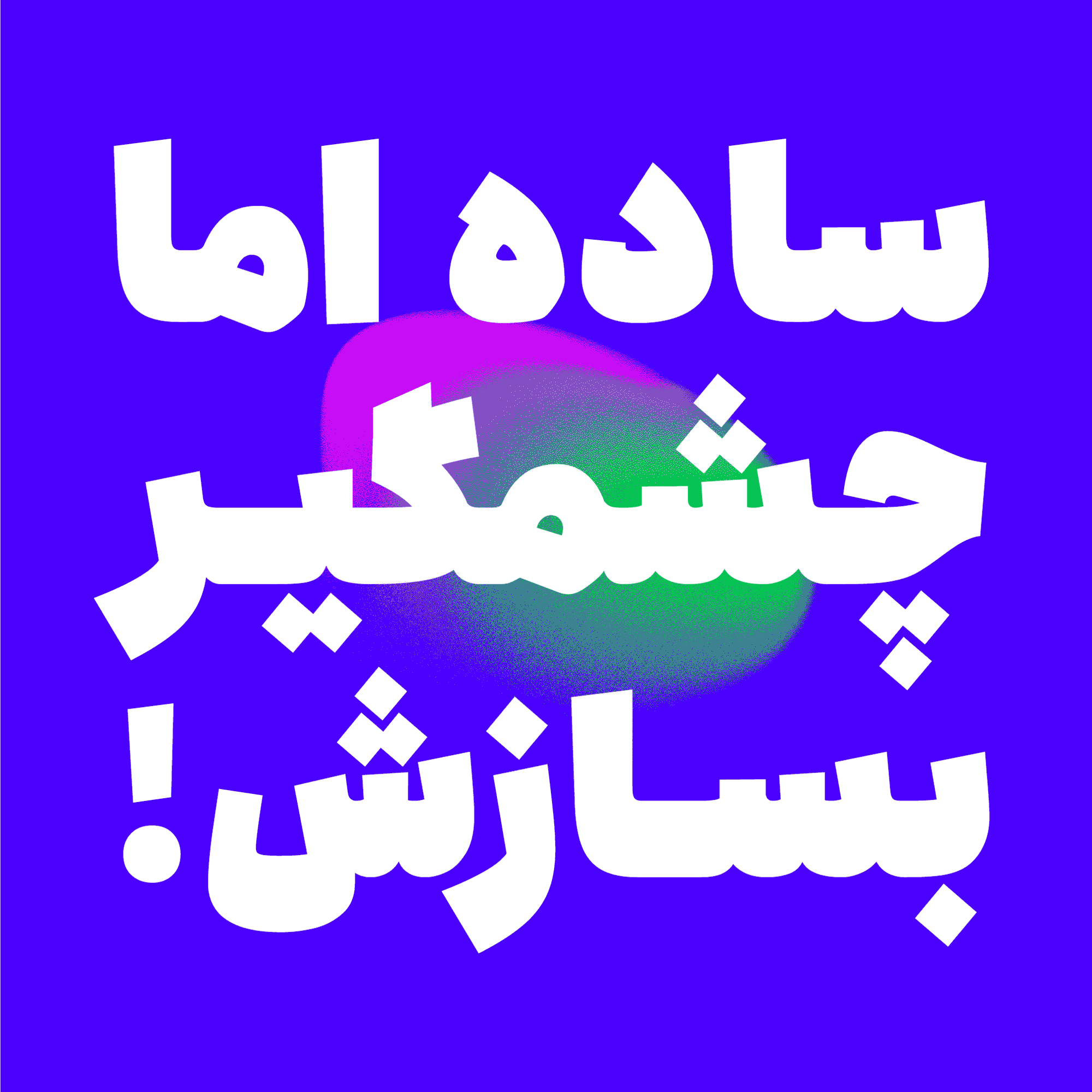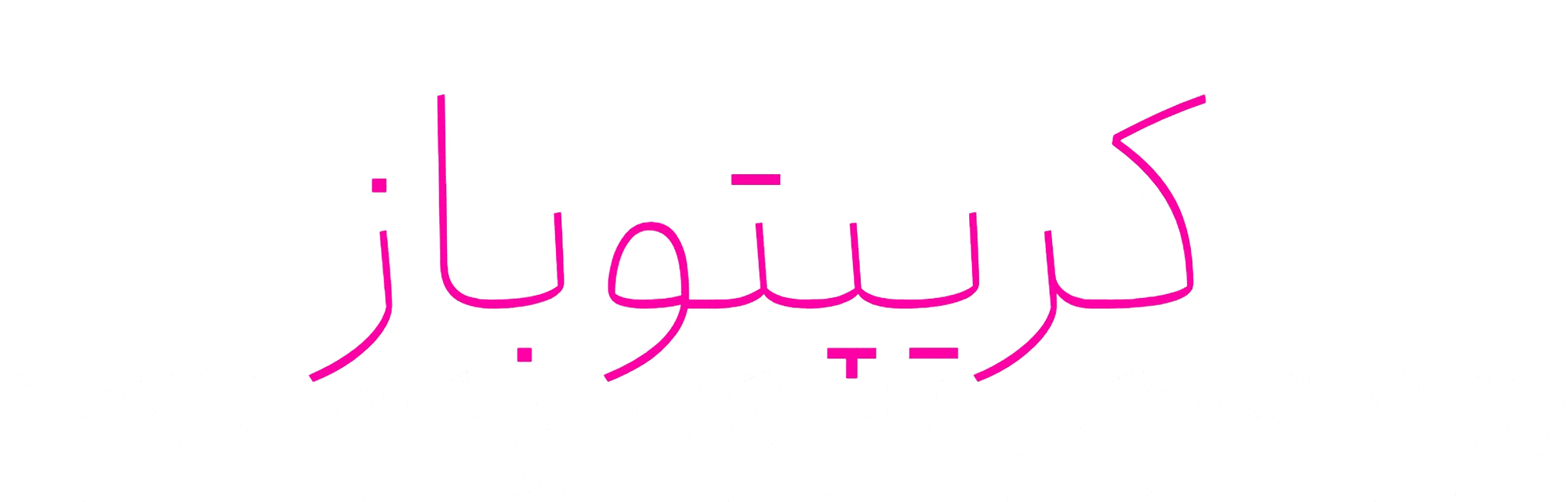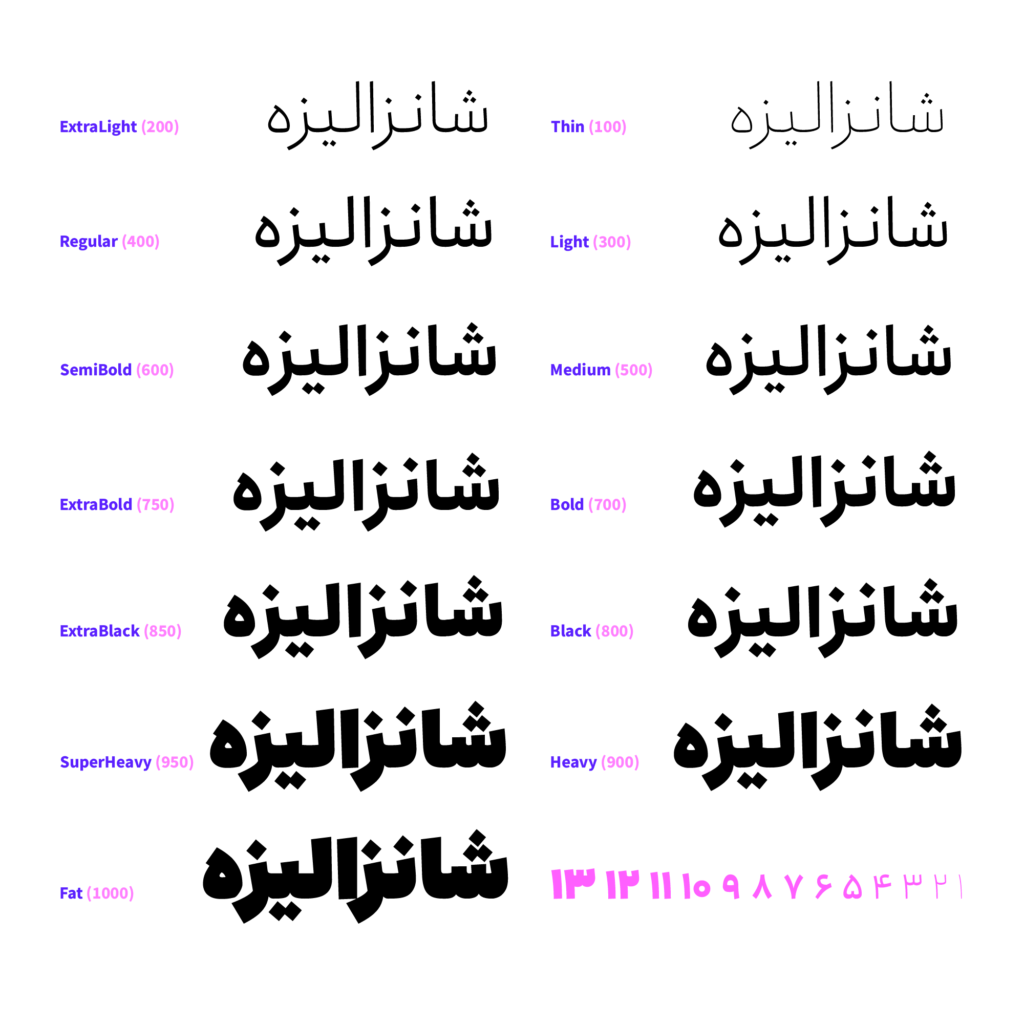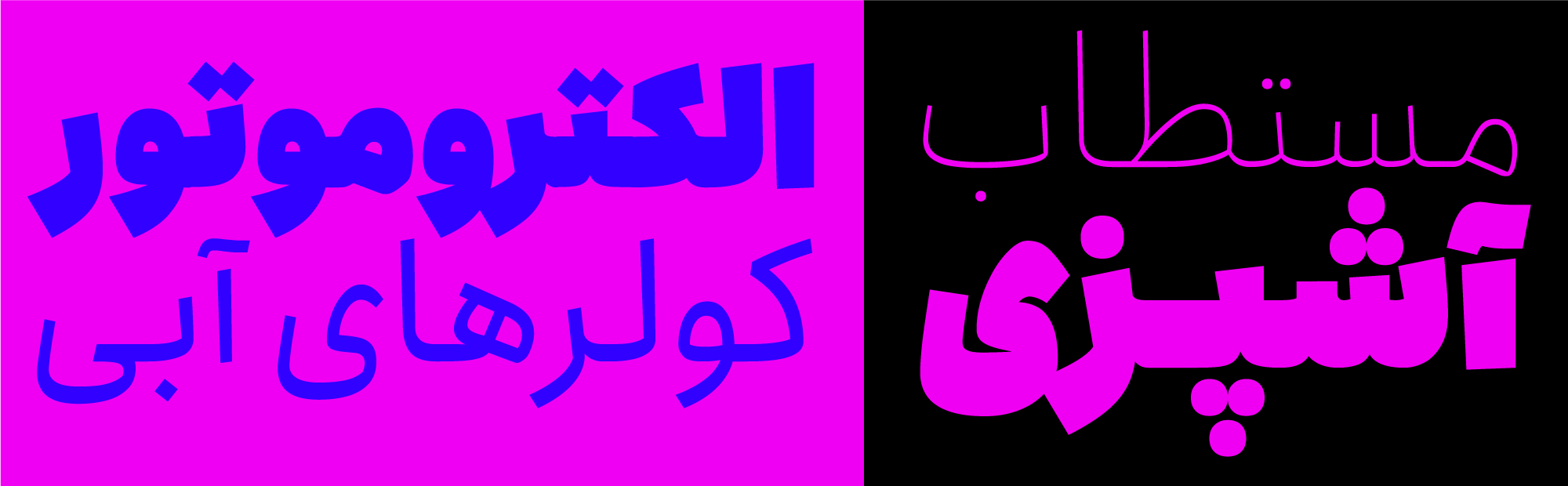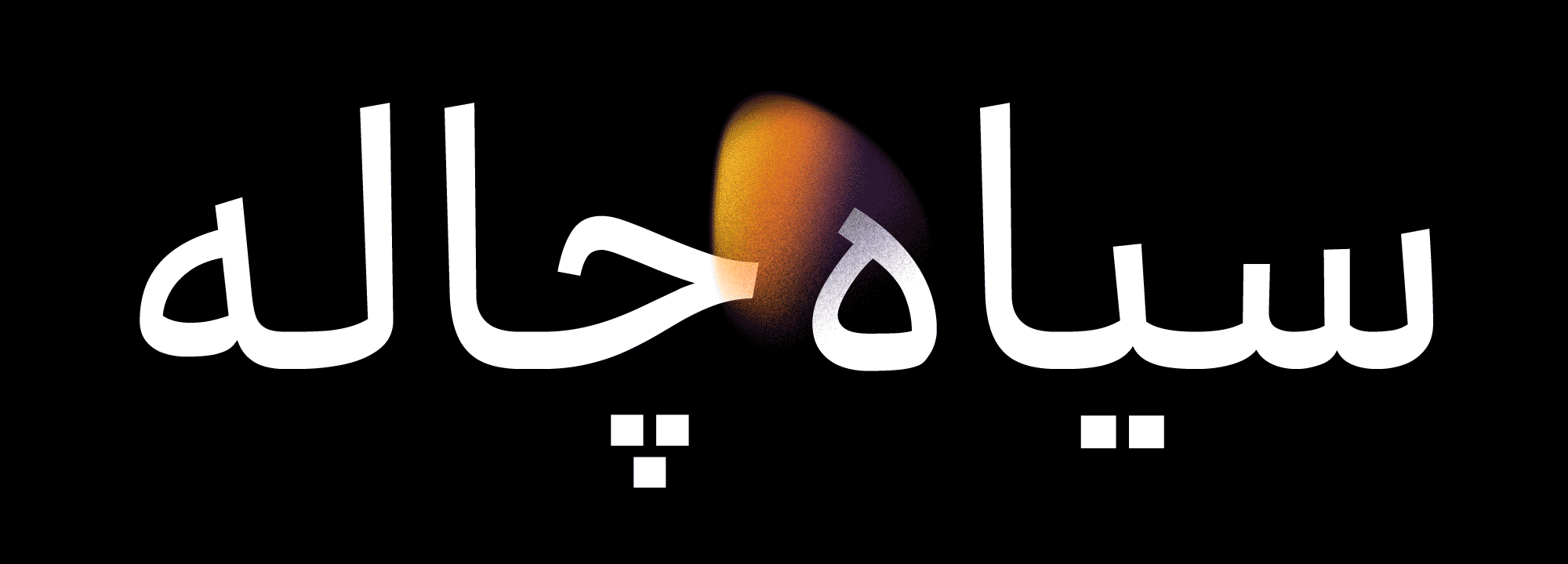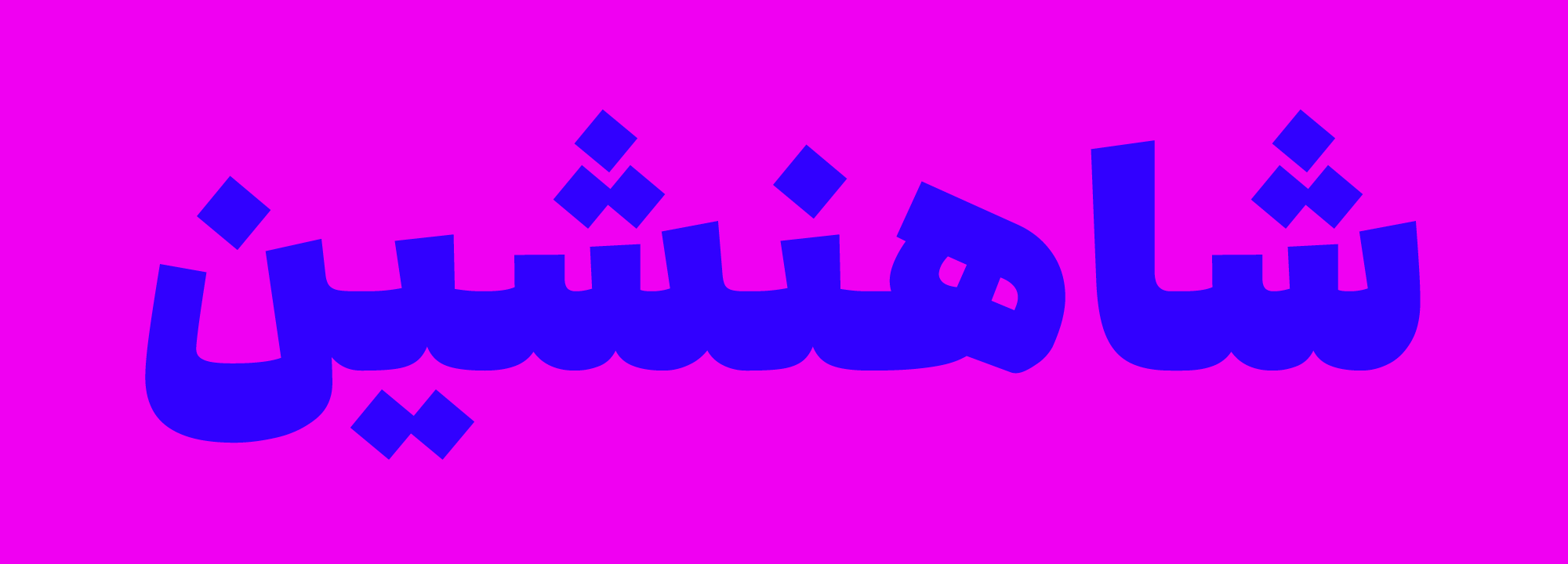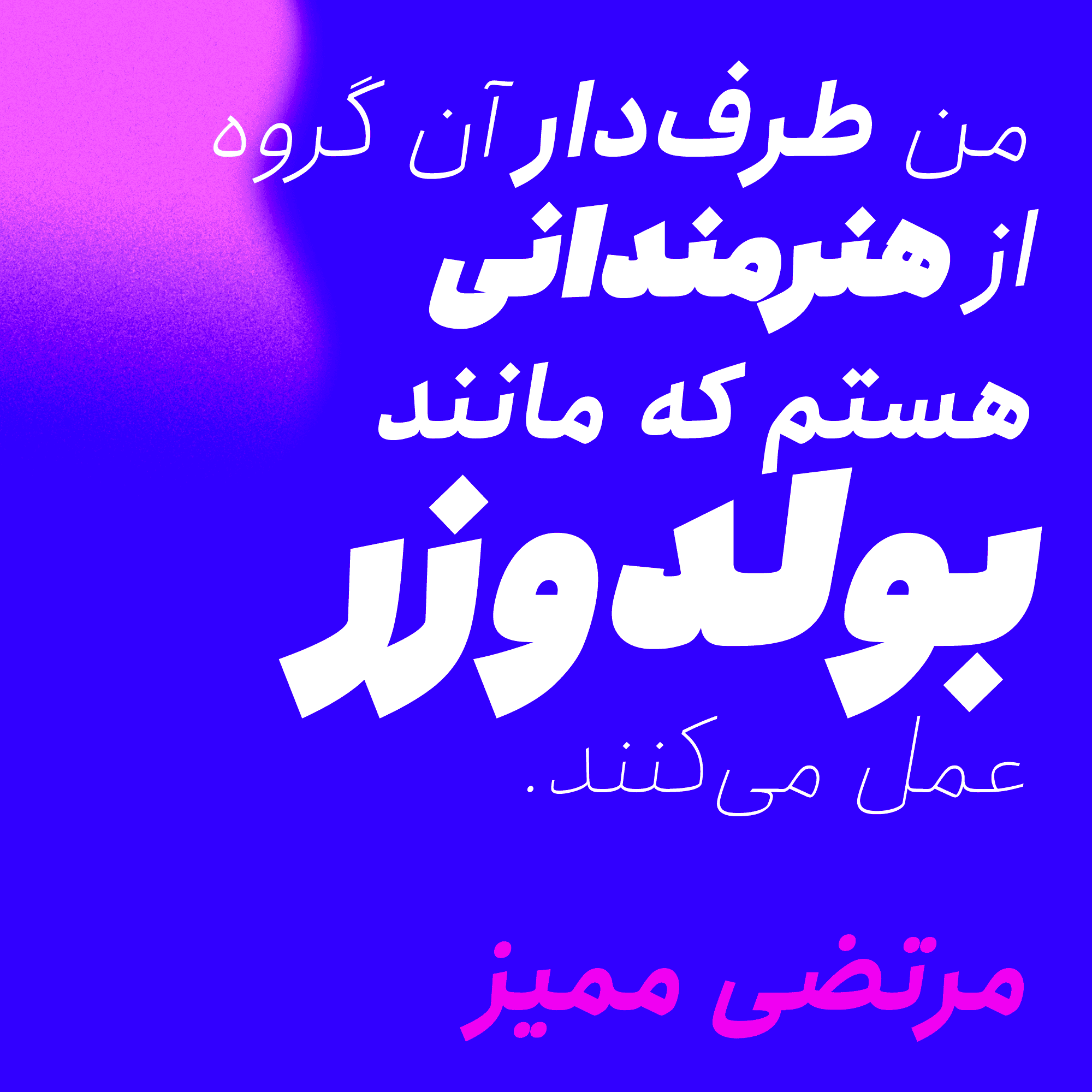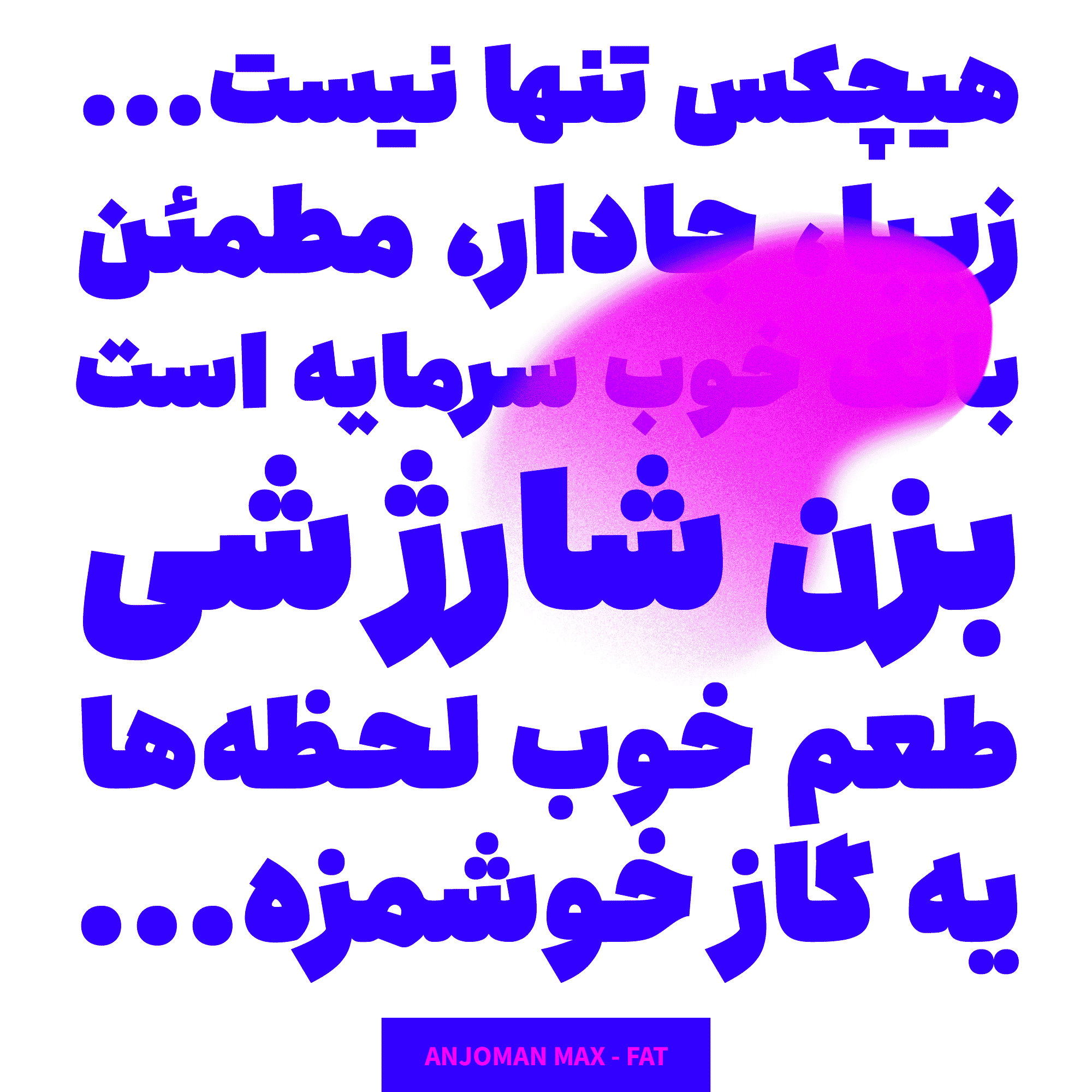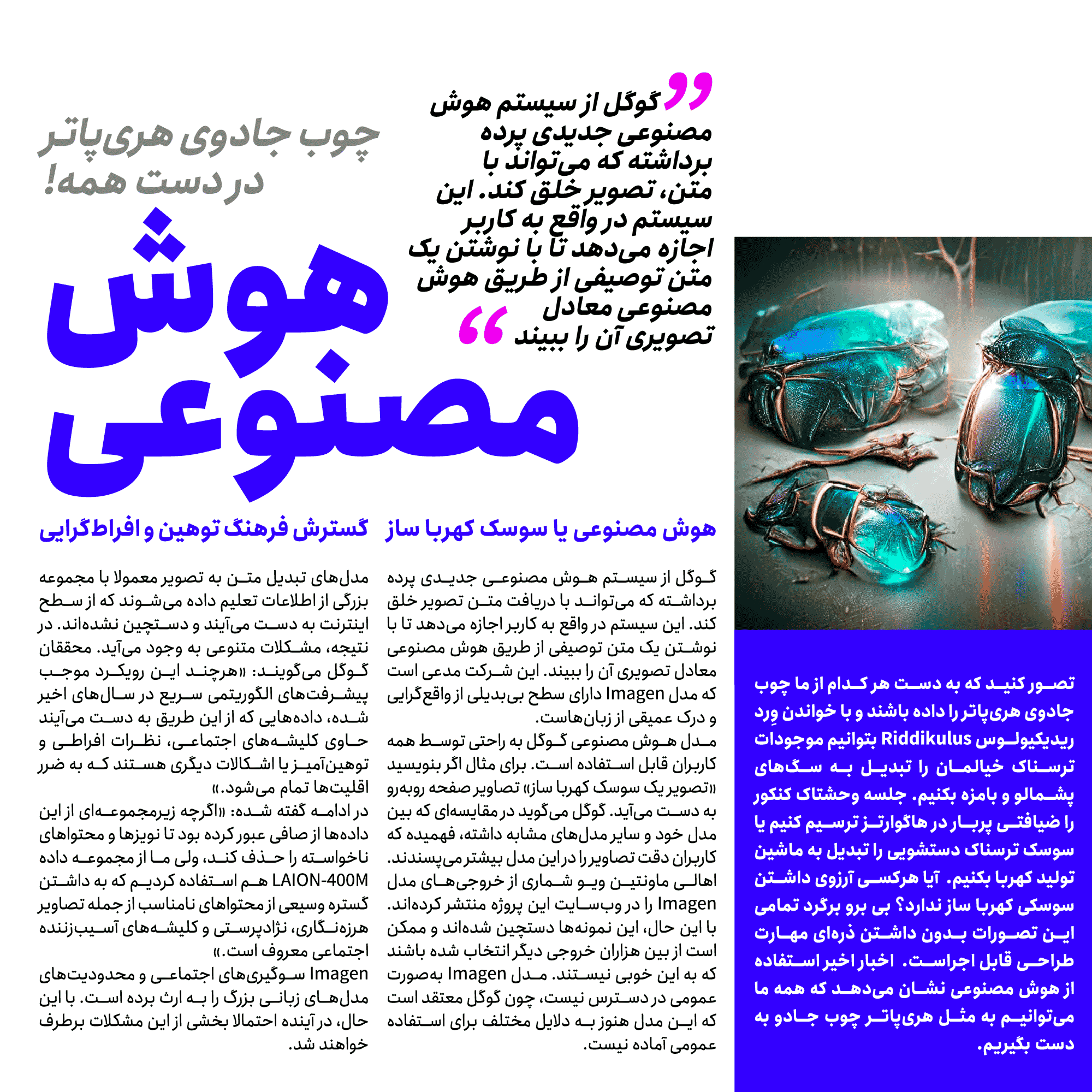
انجمن برای استفاده در رابط کاربری اپلیکیشن و سایت، گرافیک محیطی و تبلیغات، طراحی بستهبندی، صفحهآرایی و مطبوعات توسعه یافته و بهینه شده است. خانواده حروف انجمن مناسب کاربرانی است که میخواهند با یک تیر چند نشان بزنند و مجموعهای وسیع از انتخاب برای تیتر و متن داشته باشند؛ از این رو به عنوان فونت سازمانی نیز مورد استقبال قرار گرفته است.
سبک طراحی «انجمن» را میتوان معادلی نسبی برای حروف انگلیسی سنسریف دانست. از همین رو حروف انگلیسی همنشین «انجمن» با استفاده از خانواده حروف Source Sans Pro و تحت مجوز OFL توسعه یافتهاست.
انجمن مَکس تایپفیسی مدرن است که با ارائه فرمهایی ساده و ارگانیک، حالتی دلنشین از واژگان میسازد، همچنین با حفظ الگوهای آشنای خوانش، رنگی خواندنی به نوشتار میبخشد.
انجمن مکس منعطف و معتدل است؛ جایی میان سادگی و پیچیدگی ایستاده است. همچون آب در قالب طرح شما مینشیند، از این رو در مواجهه با گستره مخاطبان به خوبی نقش ایفا میکند. سادگی این فونت در انتقال سریع مفاهیم نیز کمککننده است.
تنوع وزنها؛ چاق و لاغر همدیگر را تکمیل میکنند!
لورل و هاردی، این زوج هنری همواره یکدیگر را کامل میکنند. لورل به دیده شدن هاردی و بالعکس هاردی به دیده شدن هر چه بیشتر لورل در نمایش کمک کرده است. بدون وجود دیگری نمایش ناقص خواهد بود و نقش هر یک از آنان در اجرای نمایش کلیدی است.
شما هم با در دست داشتن گستره وسیعی از وزنهای فونت انجمن، میتوانید نمایش دلخواه خود را با حروف کارگردانی کنید. خانواده حروف انجمن دارای ۱۳ وزن ( SuperHeavy ,Heavy, ExtraBlack , Black, ExtraBold, Bold, SemiBold , Medium, Regular, Light, ExtraLight, Thin و وزن جدید FAT) است که در اجرای شما به یاریتان میآید. تمامی این وزنها به همراه چهار حالت نقطههای کلاسیک، گرد، مربع و به هم پیوسته ارائه میشود. علاوه بر این پکیج فونت انجمن مَکس نسخه وریبل را هم به همراه دارد.
متغیر Weight در وریبل فونت انجمن مَکس: این متغییر وزن (ضخامت) نوشته را تعیین میکند که حداقل آن ۱۰۰ معادل وزن Thin و حداکثر آن ۱۰۰۰ معادل وزن Fat است.
متغیر Dots در وریبل فونت انجمن مَکس: این متغییر حالتهای متنوع نقطه را تعیین میکند که حداقل آن ۰ معادل نقطه کلاسیک و حداکثر آن ۳ معادل نقاط به هم چسبیده است.
قهرمان سنگین وزن!
در نسخه فونت انجمن Max یک وزن چاق (Fat) وجود دارد که برای چاق کردن آثار تبلیغاتی بسیار پُرکاربرد است! این نسخه در تبلیغات مانند بولدوزر عمل میکند!
خوانا یا خواندنی مساله این است؟
یکی از بارزترین ویژگیهای انجمن مَکس، میزان خواندنی بودن آن در مواجهه با متنهای طولانی و به هم تنیده است. انجمن مکس در تمامی وزنها با داشتن فرمهایی سالم و درست، تعیین دقیق فاصلهگذاری و تنظیم فضاهای مثبت و منفی در جهت خوانایی (Legibility) و خواندنی بودن (Readability) گام برداشته است.
سادگی سبک طراحی انجمن مکس موجب میشود تا در سایزهای مختلف همچنان خوانا باشد. با خیالی آسوده میتوانید از وزنهای نمایشی برای تیترها و از وزنهای نازکتر برای متنهای ریز و طولانی استفاده کنید.
مایل به راست اصیلتر است!
ایتالیک در فونت انجمن مَکس
برپایهی کاربرد صحیح سبک ایتالیک که برگرفته از نگاشتن پُرسرعت است، میتوان در نوشتار فارسی، خط شکسته نستعلیق را الگو قرارداد. با بررسی این حروف متوجه میشویم که به هنگام سریعنویسی در فارسی نیز قامت حروف به سمت راست مایل میشود.
حروف ایتالیک در فونت انجمن مکس بر پایه همین منطق به سمت راست مایل است. مایل بودن به سمت راست علاوه بر پیشینهای که در حروف فارسی دارد، با حروف ایتالیک لاتین نیز هماهنگتر است.
متغیر Slant در وریبل فونت انجمن مکس: این متغییر نوشتهها را تا 8 درجه ایتالیک میکند (یعنی به سمت راست مایل میکند) بنابراین حداقل آن صفر و حداکثر آن 8 است.
فشار دهید، اشکالی ندارد!
سبک فشرده (Condensed) در فونت انجمن مَکس
فشرده کردن حروف در تایپوگرافی وب و چاپ یکی از بزرگترین چالشهای دیزاینرهاست. کلمهای آن وسط له میشود و به تر و تازگی واژه آسیب میزند. موقعیتهای زیادی وجود دارد که نیاز است تا متن در یک فضای مشخص شده و غیرقابل تغییر (دکمهها در نرمافزارهای موبایل، ستونها در صفحهآرایی و …) بدون آسیب زدن به فرمها (له کردن) جا بگیرد. فونت انجمن فشرده راهحل حرفهای و سالم این وضعیتهاست؛ که با جابهجایی یک بازو (وریبل)، به راحتی آبخوردن در دسترس است.
متغیر Width در وریبل فونت انجمن مکس: این متغییر میتواند ۲۰ درصد حروف را فشرده (Condensed) کند حداقل این متغییر ۸۰ و حداکثر آن ۱۰۰ است.
هیربد لطفیان دانشآموختهی دانشکده هنرهای زیبای دانشگاه تهران، دانشجوی دوره Post Master تایپ دیزاین در فرانسه و عضو انجمن صنفی طراحان گرافیک ایران • طراحی تایپفیس «نوین» و «نوین نوآ» برای بانک اقتصاد نوین • طراحی تایپفیس «اسنپ» برای هولدینگ اسنپ • طراحی تایپفیس «بیز» برای شرکت بازاریابان ایرانیان زمین • طراحی تایپفیس «کاریزما» برای شرکت سرمایهگذاری کاریزما • طراحی تایپفیس «انجمن» و «انجمن مَکس» با حمایت انجمن صنفی طراحان گرافیک ایران دریافت نشان تایپوگرافی ممتاز آمریکا، Typ Directors Club | رتبه دوم و تقدیر ویژه Granshan | جایزه اول و سرو نقرهای ۹۸ و شایسته تقدیر سرو نقرهای ۹۲ | جایزه اول مسابقه سالانه هنر کتابآرایی